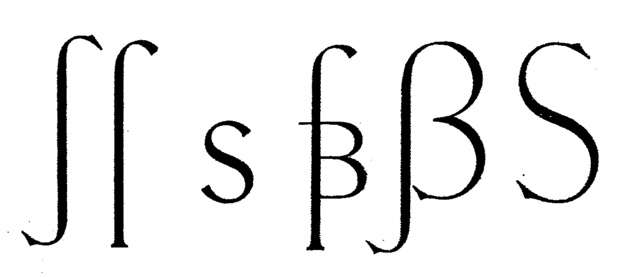
Wenn das J und eventuell das Q eine Unterlänge haben (wie es in Renaissance-Antiqua und humanistische Grotesk öfters der Fall ist) dann könnte ein Versal-ß (wenn man es dann schon macht …) eine Unterlänge haben. Wenn J und Q keine Unterlänge haben, dann ist ein Versal-ß mit Unterlänge wo möglich ein Störenfried in Layouts wo es Versalsatz mit möglichst geringer Zeilenabstand oder Versalsatz mit möglichst geringer Abstand zu Bilder, Linien usw. gibt.
Was ich mit meine Antwort bezwecken will, ist dass die Frage ob ein Versal-ß eine Unterlänge haben kann als eine stilistische Frage gesehen wird, wovon man sich die praktische Konsequenzen überlegen sollte. Ein generelles Ja oder Nein (geschweige ‘gibt’s nicht’) ist unsinnig.
… Ein generelles Ja oder Nein (geschweige ‘gibt’s nicht’) ist unsinnig.
Ich sehe das nicht als unsinnig an. Die Wahrscheinlichkeit, dass J oder Q zusammen mit ẞ mit Unterlänge mit allergrößter Wahrscheinlichkeit trotzdem ein Störenfried sein.
nicht alles was jetzt so ein klitzekleinwenig aus derReihe tanzt muß gleich ein Störenfried, kann sogar eine Bereicherung sein!
In Fraktur halte ich ihn für überflüssig, für mich ist Fraktur Geschichte, da müssen keine neuen Buchstabenformen hinzuerfunden werden.
Mal ganz abgesehen davon, dass Versalsatz in einer Fraktur sowieso eine schlechte Idee ist und auch historisch nur sehr selten (abgesehen von Worten wie Gott, Jesus, Herr und ähnlichen, die aber kein ß enthalten) verwendet wurde. Ich habe aus der Unifraktur Maguntia auch das ẞ rausgeschmissen, weil ich keinen Anwendungszweck gesehen habe, der die Investition irgeneines Aufwands in den Buchstaben rechtfertigte (und einiges an Aufwand nötig gewesen wäre um das vorhandene ẞ der Metrik der restlichen Schrift anzupassen).
Ich möchte an der Stelle auch erwähnen, dass ich das Antiqua-Versal-Eszett (in der Standardform, wenn man das so nennen kann) schon genutzt habe, ohne dass es Lesern, deren Aufgabe es war, alles Mögliche zu kritisieren, überhaupt aufgefallen ist.
Mir gefällt diese Form des großen scharfen ß.
Was anderes: Im Linn-Forum hat heute jemand auf das hier verlinkt:
Da besteht doch Korrekturbedarf (»As the ß derives from a ligature of lower-case letters, it is itself exclusively lower-case.«)!
Ich sehe das nicht als unsinnig an. Die Wahrscheinlichkeit, dass J oder Q zusammen mit [sZ][/sZ] in einem Wort vorkommen, ist verschwindend gering.
Wieso nur in einem Wort? Dass J und Q in eine Überschrift in Versalsatz vorkommen können, oder in sämtliche solcher Überschriften in einem Layout ist mir schon wahrscheinlich genug.
Man muss ja um diese Form keine Grundsatzdiskussion führen. Ich fand es interessant und zeigenswert. Vielleicht passt es ja in die eine oder andere eher beschwingt-kalligrafische Schrift in dieser Form. Das Helvetica-ẞ würd ich nun auch nicht unbedingt so zeichnen wollen.
Ich habe gerade mal einen Block vollgeschrieben – in meiner Handschrift würde sich das oben gezeigte ẞ vermutlich nur kontextbedingt einschleichen und zwar an Wortenden. Innerhalb von Worten geht das Versal-Eszett mit unterlangem linkem Strich leichter von der Hand und führt zu weniger Lesefehlern. Aber am Wortende ist die oben gezeigte Form schick. :-D
Am Wortenden … komisch, beim lang-s und rund-s ist das genau andersrum. Da wird die Form mit Oberlänge (das Pendant zur Unterlänge eines Versal-ß) nie am Ende geschrieben. Aber sei es drum, am Ende könnte es also Schriften mit zwei Versal-ß geben. Ein mit und ein ohne Unterlänge (oder Swash, egal wie man es bezeichnet). Dann sollte ein OpenType-Font einer solchen Schrift ein Feature enthalten, was sowohl das lang-s als auch das Versal-ß-mit-Unterlänge schaltet. Darüber hinaus kann man sich dann ein Regelwerk zur Verwendung des Versal-ß-mit-Unterlänge ausdenken :–)
Und damit sich das lohnt, müssen wir dringend viele neue Wörter erfinden, die ein Versal-Eszett enthalten. :cheer:
Am Wortenden … komisch, beim lang-s und rund-s ist das genau andersrum. Da wird die Form mit Oberlänge (das Pendant zur Unterlänge eines Versal-ß) nie am Ende geschrieben. Aber sei es drum, am Ende könnte es also Schriften mit zwei Versal-ß geben. Ein mit und ein ohne Unterlänge (oder Swash, egal wie man es bezeichnet). Dann sollte ein OpenType-Font einer solchen Schrift ein Feature enthalten, was sowohl das lang-s als auch das Versal-ß-mit-Unterlänge schaltet. Darüber hinaus kann man sich dann ein Regelwerk zur Verwendung des Versal-ß-mit-Unterlänge ausdenken :–)
Wenn eine Schrift sowieso kontextuelle Schwünge (?) und das Versal-Eszett enthält, wieso dann nicht kontextuelle Schwünge für das Versal-Eszett, zumal es ja tendenziell am Wortende auftritt?
Die Ober- und Unterlängen des langen s würde ich hingegen nicht als Schwünge im Sinne von End-Schwüngen ansehen. Hingegen enthält das runde s in gebrochenen Schriften oft so einen Schwung (siehe Beispiel). Eine automatische Ersetzung s→ſ ist jedoch alles andere als trivial und kann niemals vollständig korrekte Ergebnisse liefern, da das runde s auch mitten im Wort auftreten kann. Für diesen Zweck könnte man ihm natürlich den Schwung nehmen (siehe Anhang).
Ahja, dann verwirrt mich ...
... weiterhin, weil die Fraktur-Majuskel-Z ja oft Unterlängen haben, die vermutlich dem rechten Teil dieses [sZ][/sZ] ähnlicher sind als das Minuskel-z, das eher dem rechten Teil des ß in dem Bsp. ähneln dürfte ...
Ich kann dir nicht folgen. Ich habe zwei Buchstaben (ß/ẞ) gezeigt, die jeweils rechts unten einen Bogen haben, der über die Grundlinien hinausschießt. Davon sprach ich. Von z/Z war keine Rede.